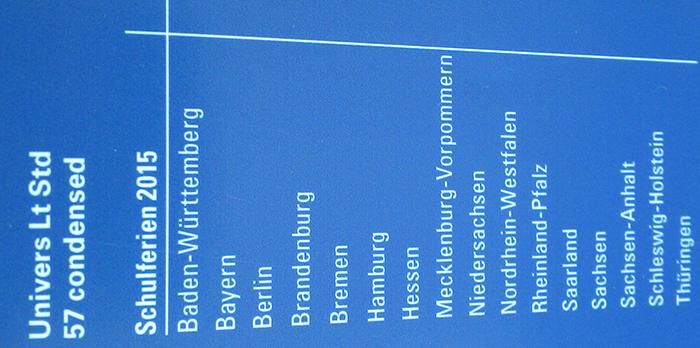
Univers 57 condensed - dickere Großbuchstaben?
ich arbeite gerade mit der Univer LT std 57 condensed auf dunklem Hintergrund in Schriftgröße 7,1 pt und da passiert beim Proofen was ganz merkwürdiges: Die groß geschriebenen Anfangsbuchstaben in einer Liste von Bundesländern sind fetter als der darauf folgende Rest der Wörter in kleinbuchstaben.
Ist das schonmal jmd aufgefallen?
Ich hab etliche Tests gemacht: Proofer gewechselt. Unterschiedliche Anbieter der condensed ausprobiert. Schriftgröße verändert. Immer ist es zu sehen. Kann sowas sein, dass eine solch renomierte Schrift so komisch geschnitten ist?
Hier mal der Versuch es euch zu zeigen, ein Foto vom Proof im Anhang.
Der Unterschied der Strichstärke von den Versalien zu den Kleinbuchstaben beträgt bei der Univers ca. 10 Prozent.
Das ist vom Schriftgestalter so gewollt und liegt nicht am Drucker.
Wenn dies zu deiner Gestaltung nicht passt, solltest du eine andere Schrift, mit weniger Linienstärken-Unterschied verwenden.
Im Prinzip ist das bei allen Textschriften so, da sonst die Großbuchstaben zu mager wirken würden. Sie sind eben größer und haben meist auch mehr »Luft« in sich. Deswegen vergrößert man die Strichstärke, um einen optischen Ausgleich zu erzielen.
Je nach Schrift ist das mehr oder weniger deutlich ausgeprägt.